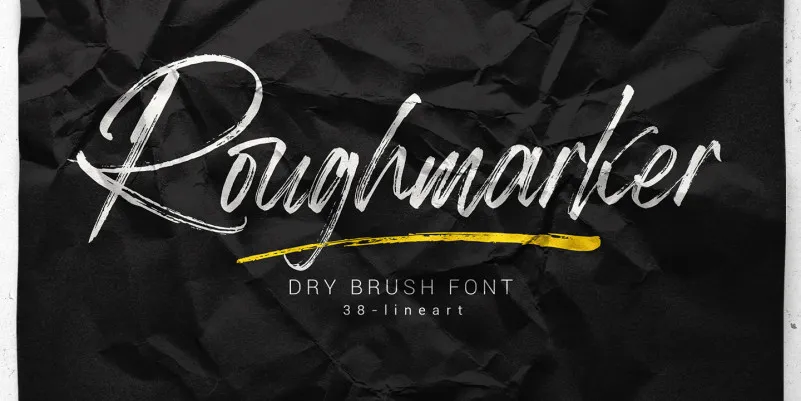
Roughmarker Brush Font – Download Grátis
Roughmarker Brush Font é uma elegante escolha para designers em busca de um estilo inconfundível e moderno que se destaca no cenário de design atual. Com duas versões escritas à mão – uma inclinada (regular) e outra vertical – esta fonte oferece a flexibilidade necessária para adaptar-se às diferentes necessidades do seu projeto. Ideal para empresas atemporais interessadas em temas como moda, estilo urbano, arquitetura de vanguarda, maquiagem moderna ou um lifestyle animado, esta fonte possui uma layout tipográfico chamativo que a torna particularmente atraente e premium. O resultado é um design gráfico enriquecido e sofisticado, ideal para criar mensagens poderosas e influentes em sua próxima peça de marketing digital ou produto. Através do uso desta fonte Roughmarker Brush Font, você pode oferecer uma versão única e memorável aos seus clientes sem perder a personalidade que seu negócio se destaca.